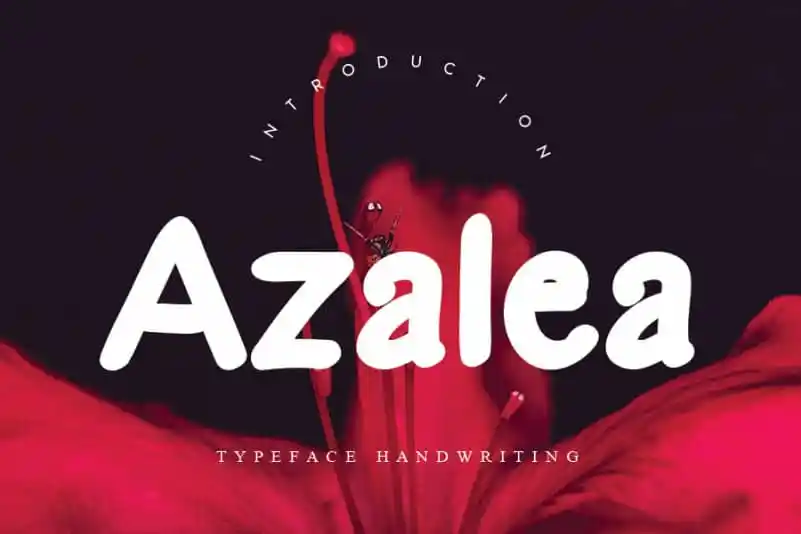
A Azalea Handwritten Font é uma escolha perfeita para quem procura um estilo único e pessoal no seu design digital. Essa fonte é definida por sua escrita livre, com traços ressaltados de forma cuidadosamente elaborada para oferecer resultados incrivelmente atraentes. Ela é ideal tanto para seus logotipos quanto para o seu trabalho de marca, redes sociais e até mesmo suas projetos DIY criativos. Com um ar moderno que se mantém ao mesmo tempo romântico e divertido, esta fonte adquire uma característica única – uma leve originalidade. Ela é perfeita para aqueles que buscam dar um toque personalizado em seus designs digitais, oferecendo um ar único que traz seu projeto para o topo. Este é definitivamente um recurso gráfico valioso e criativo para qualquer designer ou desenvolvedor de sites.